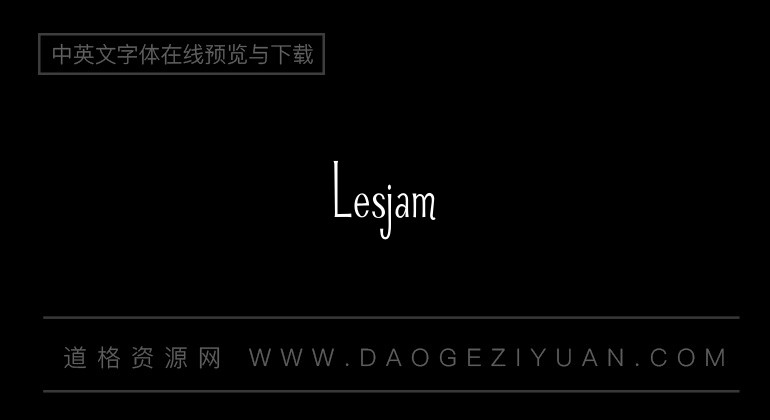
Lesjam
吧 Lesjam 字体是一种新的英文字体,它融合了日式和西方的设计元素,以便更好地表达文字的多样性。Lesjam 字体的字体设计灵感来自日本传统的折纸艺术,以及西方的谐调字体设计,并采用了英文和日文字体的特点,使字体更加清晰、精致、优雅。Lesjam 字体具有良好的可读性,它的设计可以帮助读者更好地理解文字的含义,从而提高文字的可读性。
Lesjam是一款非常不错的手写艺术字体,具有很好的视觉感,适合于文化类的宣传设计、商业类品牌的广告和产品包装设计以及个性化文字排版等较多场景。